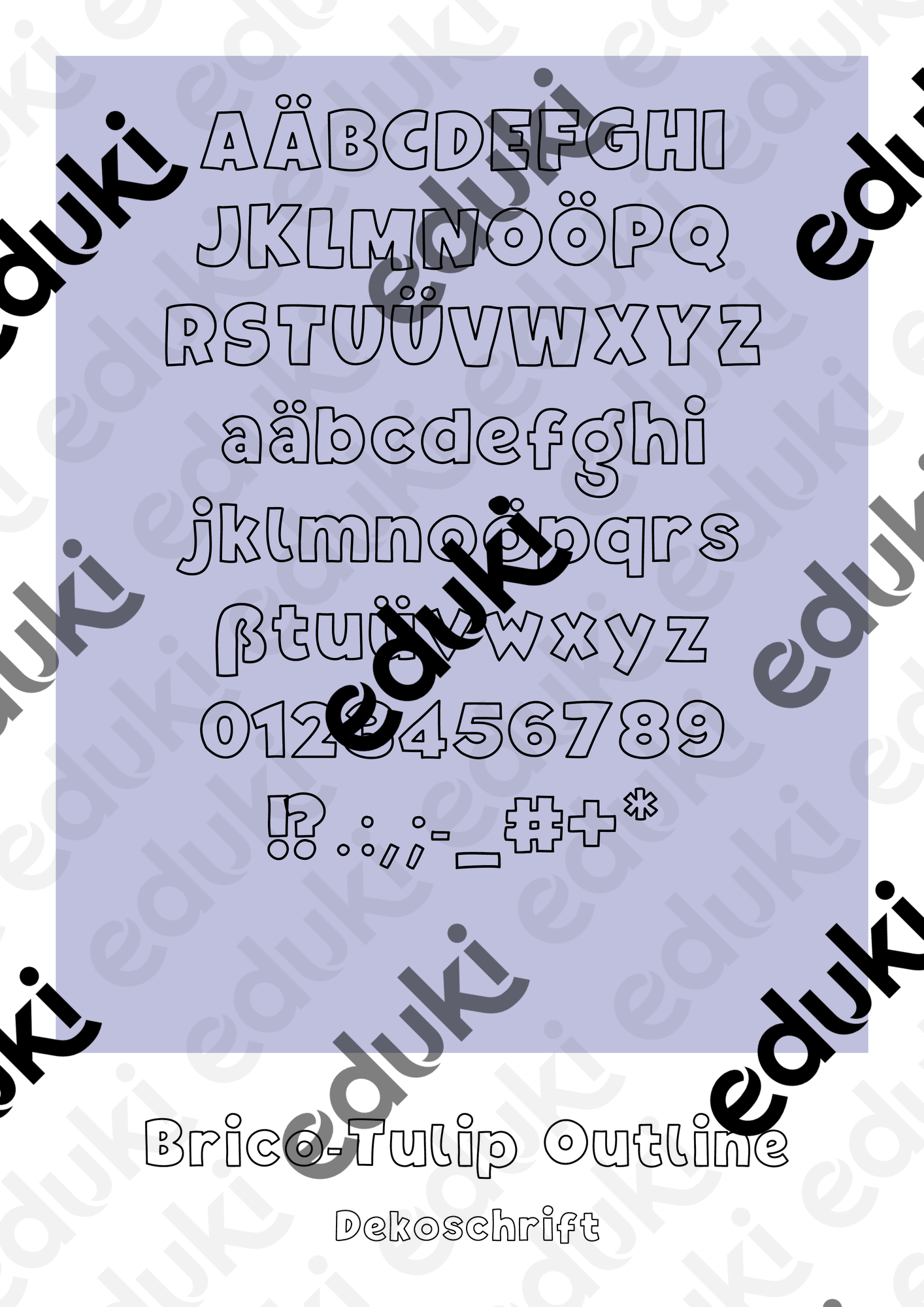
Selbsterstellte Dekoschrift die sich wunderbar zur Erstellung von Arbeitsblättern oder anderem Unterrichtsmaterial eignet.
Schriftart für dein Arbeitsmaterial - BricoTulipOutline